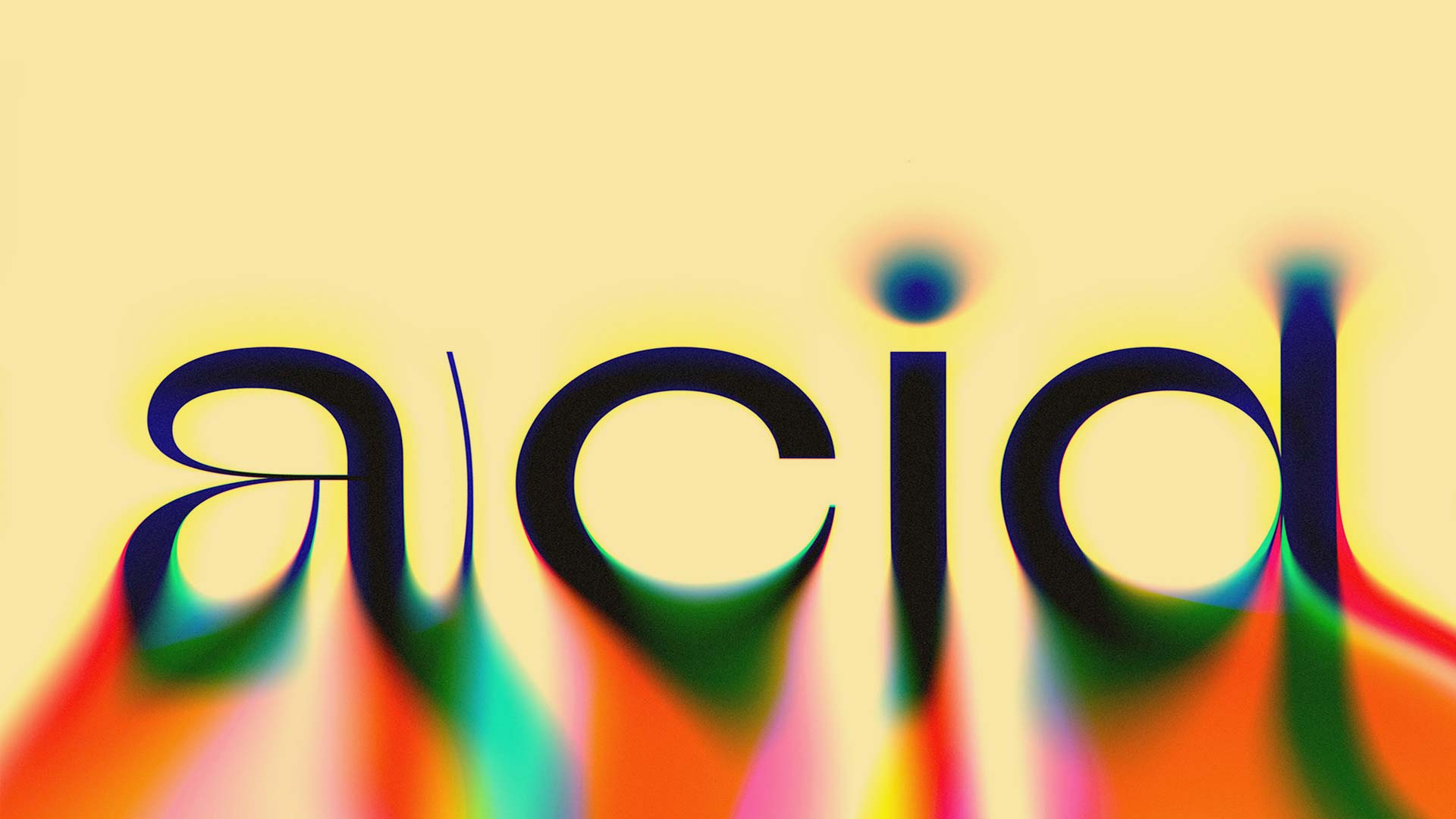
Die 7 spannendsten Typografie-Trends im Grafikdesign für 2023.
Von modernen Serifen bis hin zu experimentellen Schriftarten - entdecken Sie die neuesten Entwicklungen in der Typografie 2023.
Typografie spielt eine wichtige Rolle im Grafikdesign und hat in den letzten Jahren eine enorme Entwicklung durchgemacht. Von der Wahl der richtigen Schriftart bis hin zur Anordnung von Texten kann Typografie die Tonalität und Stimmung eines Designs stark beeinflussen.
In diesem Artikel werfen wir einen Blick auf die 7 wichtigsten Typografie-Trends im Grafikdesign 2023 und geben Ideen, wie auch Sie diese für Ihr Branding einsetzen können.
1. Expressive Typografie
Ausdrucksstarke Typografie ist einer der bestimmenden Trends des Jahres 2023 im Grafikdesign. Diese Art von Typografie wird verwendet, um eine starke visuelle Wirkung zu erzielen und eine klare Botschaft zu vermitteln.
Bei der ausdrucksstarken Typografie werden häufig fette, übergroße Schriftarten und leuchtende Farben verwendet, um die Aufmerksamkeit auf den Text zu lenken. Richtig eingesetzt, kann die ausdrucksstarke Typografie dazu beitragen, ein auffälliges Design zu schaffen. Sie wird oft mit abstrakten Formen und Mustern, lebhaften Farbverläufen und dynamischen Illustrationen kombiniert. Sie kann auch in Kombination mit anderen Typografie-Trends wie minimalistischen oder Retro-Schriften verwendet werden, um ein einzigartiges und modernes Aussehen zu schaffen.
2. Serifen Fonts
Serifenschriften, zu denen Schriftarten wie Times New Roman und Georgia gehören, erleben im Jahr 2023 ein großes Comeback im Grafikdesign. Die Verwendung von diesen Schriften kann einem Design eine klassische und zeitlose Note verleihen.
Moderne Serifenschriften haben eine klare, schlanke Form und eignen sich besonders gut für große Überschriften. Dicke Serifenschriften haben eine starke Präsenz und sind perfekt für den Einsatz als Haupttypografie geeignet. Eine neue Interpretation von klassischen Serifenschriften kombiniert die traditionelle Form mit modernen Elementen wie abgerundeten Ecken oder asymmetrischen Serifen.
Um eine Serifenschrift in einem Design optimal zu nutzen, ist es wichtig, die Farbpalette und die verwendeten Designelemente zu berücksichtigen. Klassische Schwarz-Weiß-Farbschemata passen gut zu Serifen Fonts, ebenso wie gedämpfte und natürliche Töne. Für einen modernen Akzent kann die Kombination mit einer serifenlosen Schrift oder anderen Gestaltungselementen wie Farben, Muster, Fotos und Illustrationen ein zeitloses und einzigartiges Erscheinungsbild schaffen.
3. Bold Minimalismus
Beim Typografie-Trend "Bold Minimalismus" geht es darum, mit weniger Wörtern und größeren Schriftarten ein Statement zu setzen. Es geht um die Verwendung von fetten, klaren Schriften in einem minimalen, sauberen und modernen Design. Dieser Trend wird oft in Kombination mit einer gedeckten, aber hellen und lebendigen Farbpalette verwendet. Dieser Look ist ideal, um jedem Designprojekt ein modernes, hochwertiges Aussehen zu verleihen.
Bei der Verwendung von Bold Minimalismus ist es wichtig, die Wirkung zu bedenken, die er in Kombination mit anderen Designelementen haben kann. Zum Beispiel kann die Kombination mit einer dünnen serifenlosen Schrift und dünnen Linien eine starke, minimalistische Ästhetik erzeugen. Das Hinzufügen einiger subtiler Texturen und Farbverläufe im Hintergrund kann dem Design Tiefe und Dimension verleihen. Schließlich kann ein Hauch von Metallic oder stark gesättigten Farben dazu beitragen, den kühnen Minimalismus zum Leben zu erwecken.
Der beste Weg, den Bold Minimalismus zu verwenden, ist, das Gesamtdesign sauber und modern zu halten und dabei sicherzustellen, dass der Schwerpunkt auf der dicken Schrift liegt.
4. Flux
Der Trend "Flux" hat in den letzten Jahren immer mehr an Popularität gewonnen und setzt sich auch 2023 fort. Bei diesem Trend werden dynamische und lebendige Schriftarten verwendet, um einen energiegeladenen und ansprechenden Look zu schaffen. Flux-Schriften werden oft mit modernen, minimalistischen Designelementen wie geometrischen Formen und flachen Farben kombiniert. Die Kombination dieser Elemente sorgt für einen eleganten und eindrucksvollen Look.
Bei diesen Layouts ist es wichtig, das Gesamtdesign ausgewogen zu halten, um den Betrachter nicht zu überfordern. Marken sollten mit verschiedenen Kombinationen von Schriftarten, Farben und anderen Designelementen experimentieren, um ein optisch ansprechendes und modernes Design zu erzeugen.
5. Experimentelle Fonts
Experimentelle Schriftarten im Grafikdesign haben in den letzten Jahren stark an Popularität gewonnen, das Jahr 2023 wird da keine Ausnahme sein. Diese Schriftarten sind oft abstrakt und erlauben es, neue und aufregende Formen zu erkunden.
Bei der Verwendung experimenteller Schriftarten empfiehlt es sich, diese mit anderen, eher traditionellen Designelementen zu kombinieren, z. B. mit klassischen Serifen Fonts oder geometrischen serifenlosen Schriften. Außerdem sollte man darauf achten, Farben zu verwenden, die die experimentelle Schrift ergänzen und nicht mit dem Design kollidieren. Eine helle und kräftige Schriftart eignet sich zum Beispiel am besten in Kombination mit sanfteren, gedeckten Farben. Richtig eingesetzt, können experimentelle Schriftarten eine großartige Möglichkeit sein, ein Design von der Masse abzuheben.